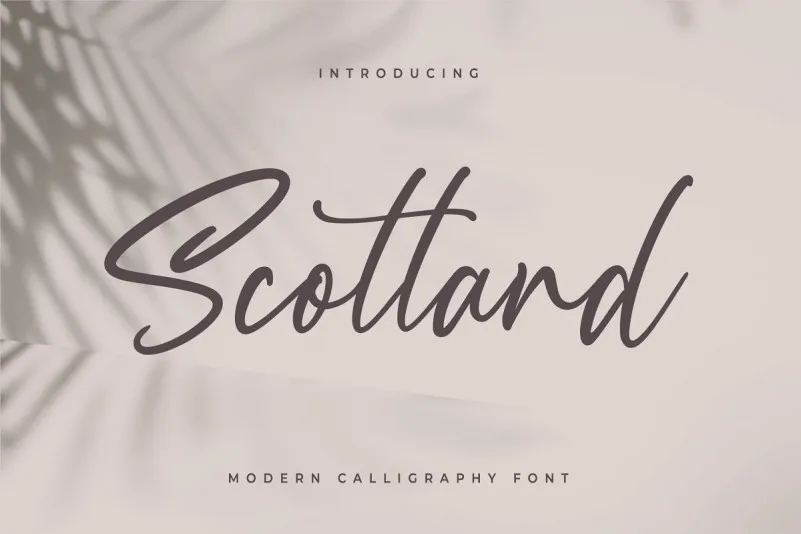
Scotland Calligraphy Font – Download Grátis
Introduzimos uma nova fonte de calligrafia fresca e handmade. A fonte inspirada na escrita manual “Unique handmade calligraphic Inspiration Hand Drawn Font” oferece um look moderno, combinado com a adição de traços alternativos tanto nos caracteres maiúsculos quanto minúsculos. Este é um fonte de calligrafia especial. “Scotland Calligraphy” é perfeito para marcas de marca, convites para casamento e cartões, até mesmo rótulos de vinho. Esta font vem com um conjunto completo de letras maiúsculas e minúsculas, símbolos multilíngues, números e pontuação. Sem dúvida, uma opção ideal para quem busca expressar sua marca em um estilo elegante e único.